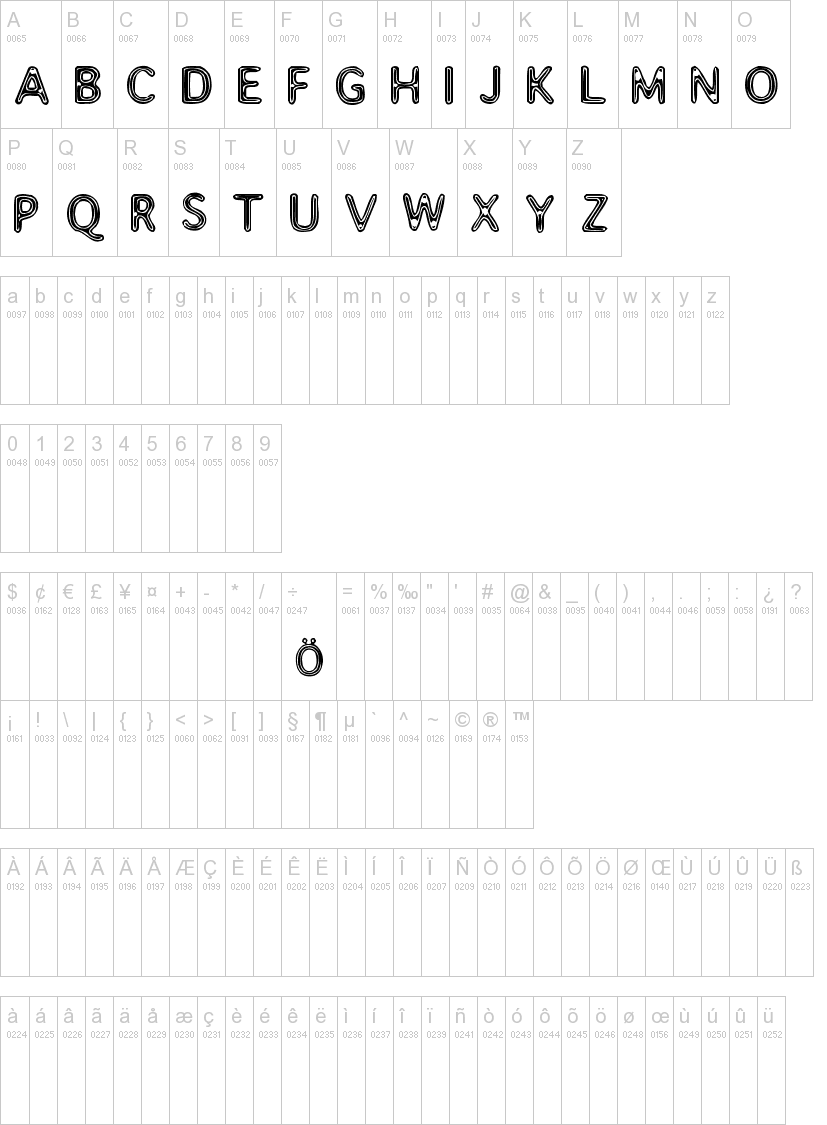
Assimilate 字体是一款现代多功能字体,由 Fontfabric 字体工作室设计,具有超大的字体变体。该字体具有简洁的外观,适合用于任何类型的设计,包括标题、标签、网页、印刷等。Assimilate 字体具有超大的字体变体,支持多种文字样式,如粗体、斜体、细体等,可以满足不同的设计需求。内容介绍
Assimilate是一款非常不错的手写艺术字体,具有很好的视觉感,适合于文化类的宣传设计、商业类品牌的广告和产品包装设计以及个性化文字排版等较多场景。